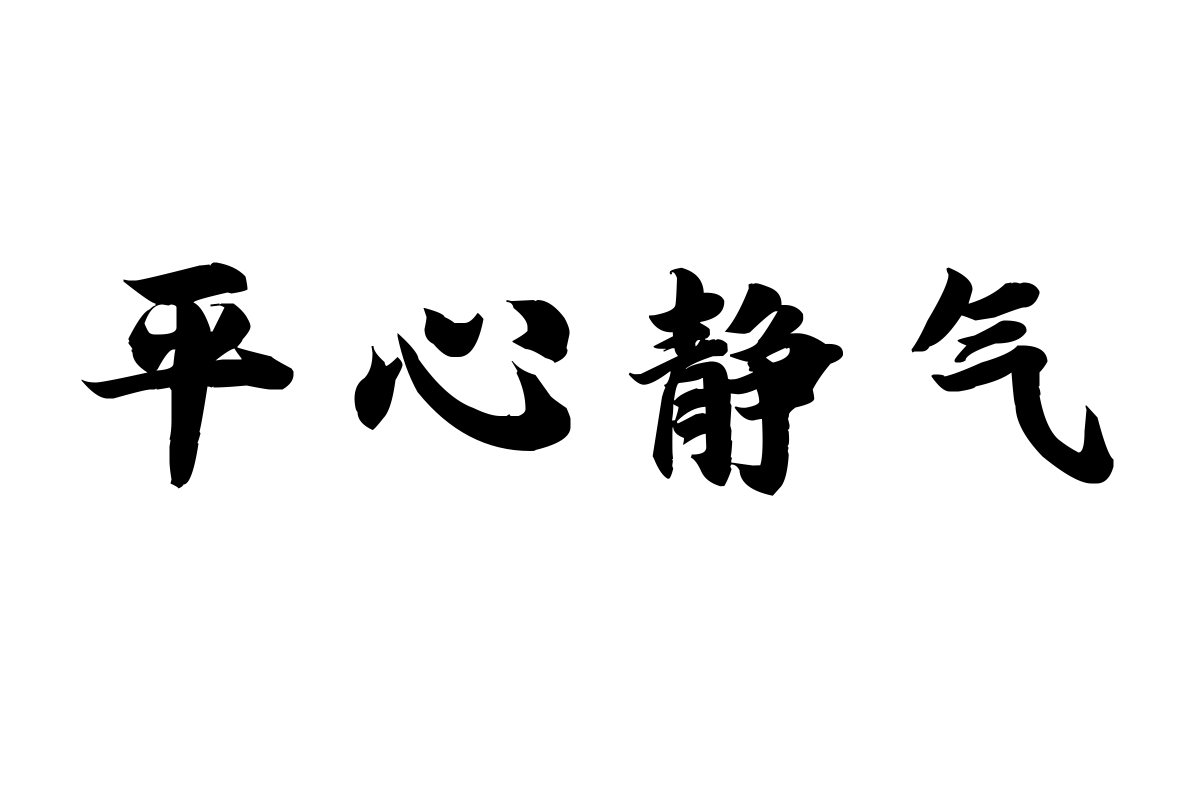
汉呈王天喜榜书是汉字书法的一种风格,属于行书范畴。这种字体的特点是笔画流畅,结构紧凑,既有楷书的规整,又有草书的灵动。其特点包括:
1. 笔画流畅:汉呈王天喜榜书的笔画线条流畅,没有太多的停顿和顿挫,给人一种行云流水的感觉。
2. 结构紧凑:虽然笔画流畅,但汉呈王天喜榜书的结构却非常紧凑,每个字的笔画都恰到好处地分布在整个字的空间内,使得整个字体看起来既美观又大方。
3. 规整与灵动相结合:汉呈王天喜榜书既有楷书的规整,又有草书的灵动。楷书的规整体现在每个字的笔画都严格按照一定的顺序和规则进行排列,而草书的灵动则体现在笔画的起笔、收笔和转折处的变化。
4. 个性鲜明:由于汉呈王天喜榜书的笔画流畅、结构紧凑,所以书写者可以根据自己的喜好和习惯,创造出独特的个人风格,使整个字体充满了个性和魅力。